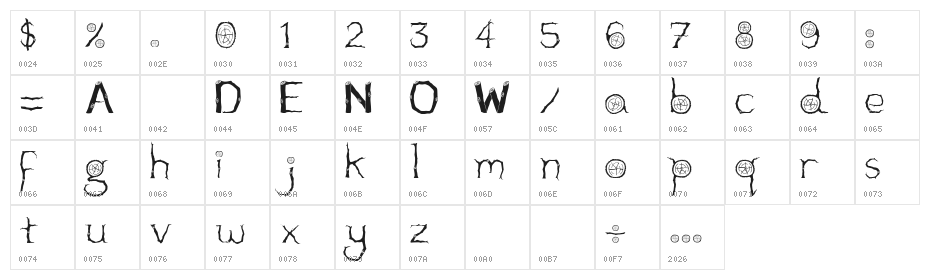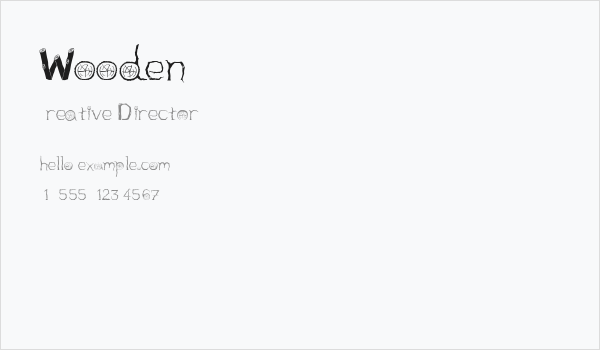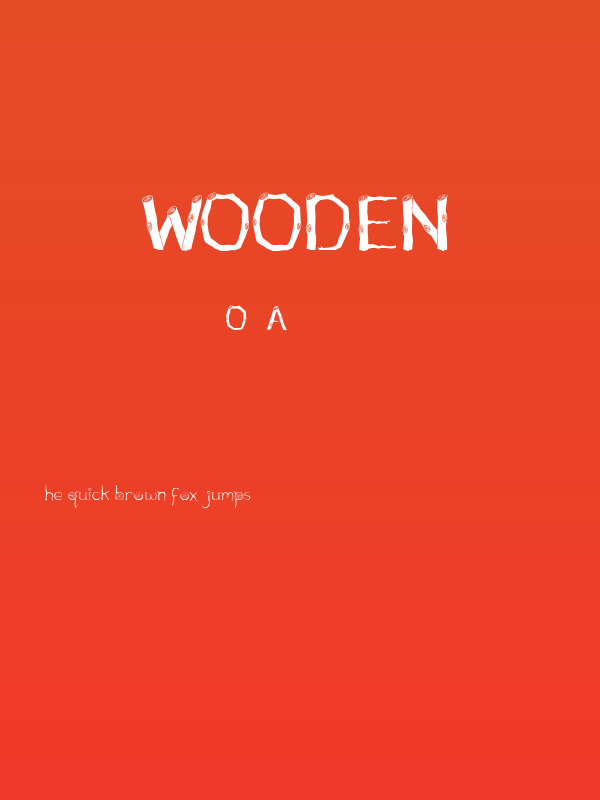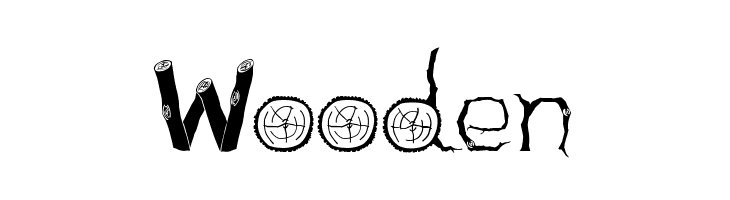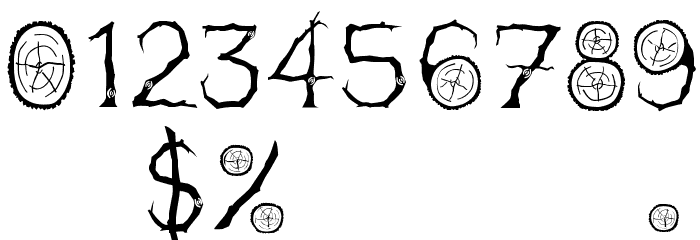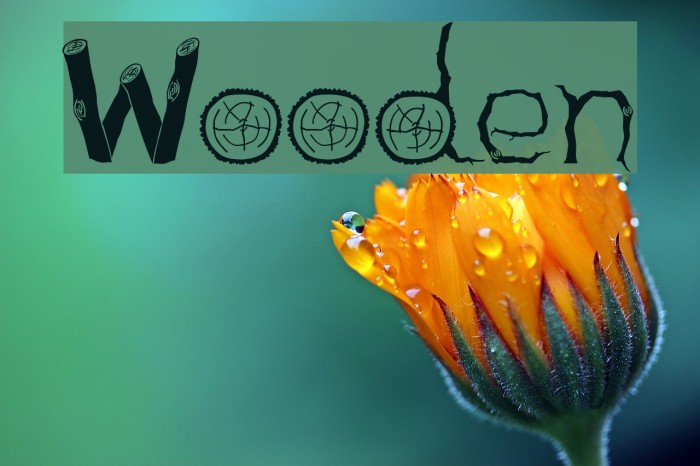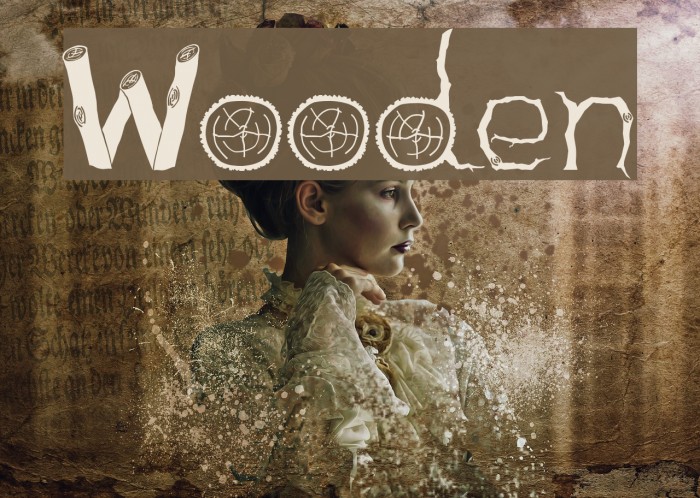
Wooden Font
✎ Decorative
| Caso de uso | Logos, Headlines, Themed Invitations |
| Proyectos propuestos | Ideal for eco-friendly branding, rustic event invitations, and outdoor-themed designs. |